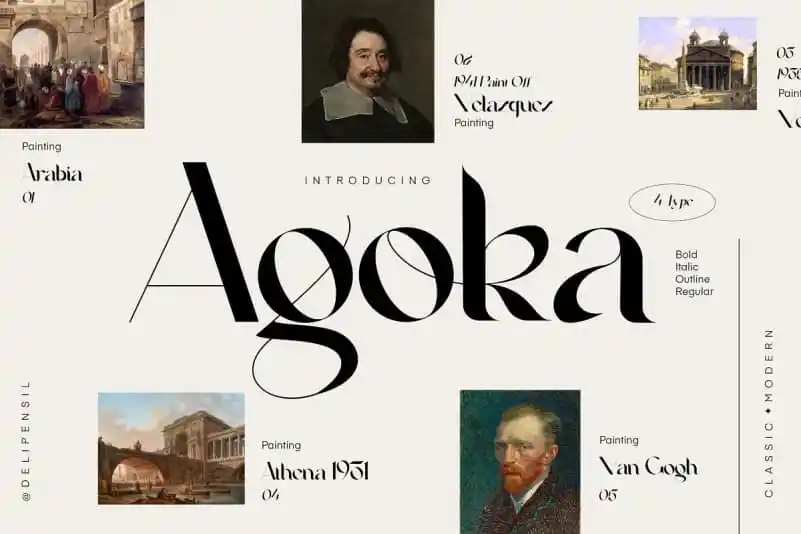
Agoka Serif Font
A Agoka Serif Font é uma tipografia serif clássica criada por delipensil, repleta de alternativas e ligaturas que remetem ao passado. Esta elegante tipo de letra serif combina um toque sofisticado com uma aparência limpa e pensativa. Perfeita tanto para logos quanto para headlines, capas de livros, revistas e sites, a Agoka Serif é versátil o suficiente para atender às mais diversas necessidades de design. Seja você designer ou criativo, esta fonte oferece uma abordagem moderna ao manuseio dos elementos serif que fazem parte do design tradicional. Suas alternativas e ligaturas permitem experimentar diferentes combinações que refletem um resgate às antigas estéticas, oferecendo também a liberdade para você expressar sua criatividade de maneira única. A Agoka Serif é uma ótima escolha para quem busca adicionar algum toque vintage e sofisticado em seus projetos. Seja para um design de logomarca minimalista ou para o texto de capa de um livro, a Agoka oferece uma mistura perfeita de elegância e funcionalidade que se alinha com todos os tipos de aplicativos digitais modernos. Adquirindo a Agoka Serif Font, você não está apenas adquirindo mais uma fonte, mas também uma ferramenta poderosa para expressar seu trabalho através do uso de estilos serif clássicos. Estamos ansiosos para vê-lo trazer vida e charme aos seus projetos com esta fonte única e versátil.